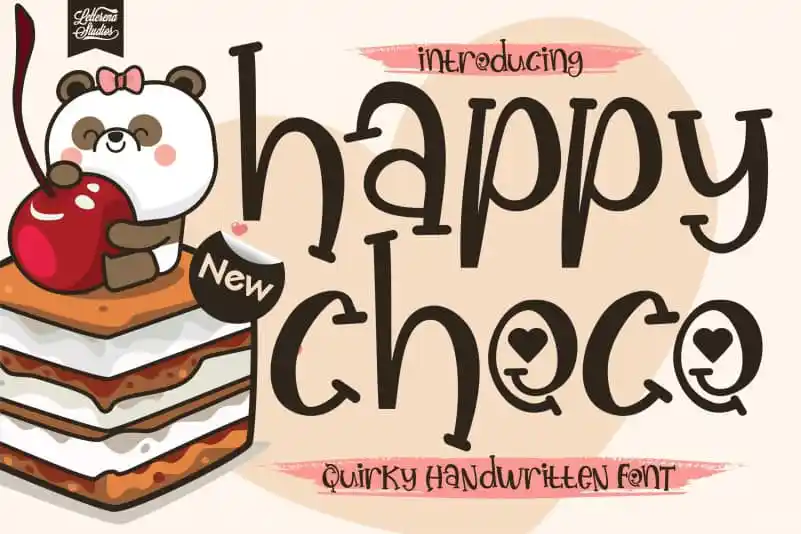
A Happy Choco Display Font é uma fonte feita à mão com estilo único. Ela carrega aquela pitada de quirkiness que faz as pessoas sorrir, especialmente a quem aprecia designs infantis ou projetos culinários leves e encantadores para crianças. Se você busca adicionar um toque de brincadeira aos seus trabalhos gráficos, essa fonte é perfeita. Suas letras dançantes são certamente uma delícia de usar em design infantil ou em qualquer projeto relacionado a doces gostosos, como embalagens de chocolate ou decoração de festa de aniversário para crianças. A Happy Choco Display Font não só enriquece seus trabalhos gráficos, mas também encanta sua audiência de maneira encantadora e envolvente.